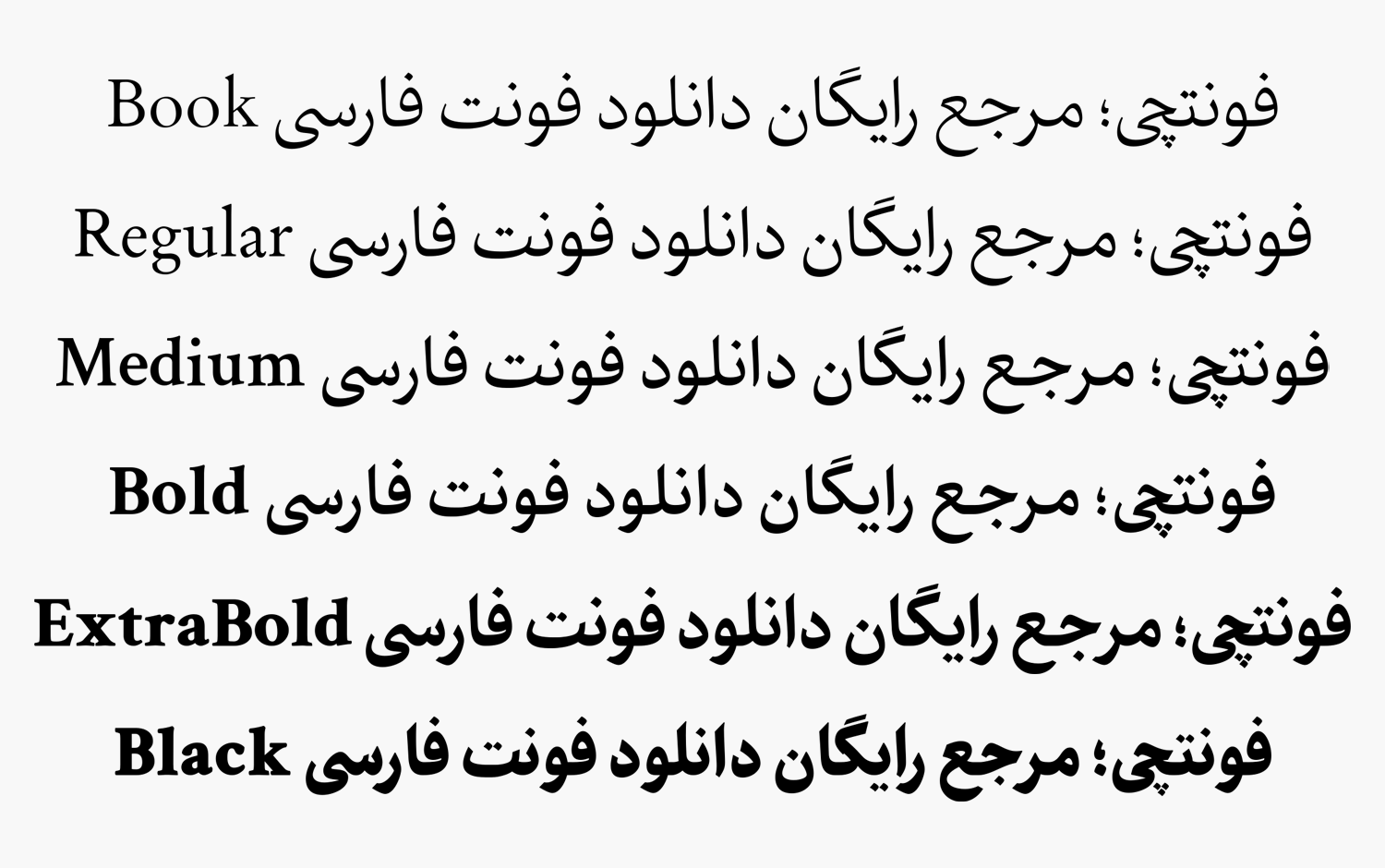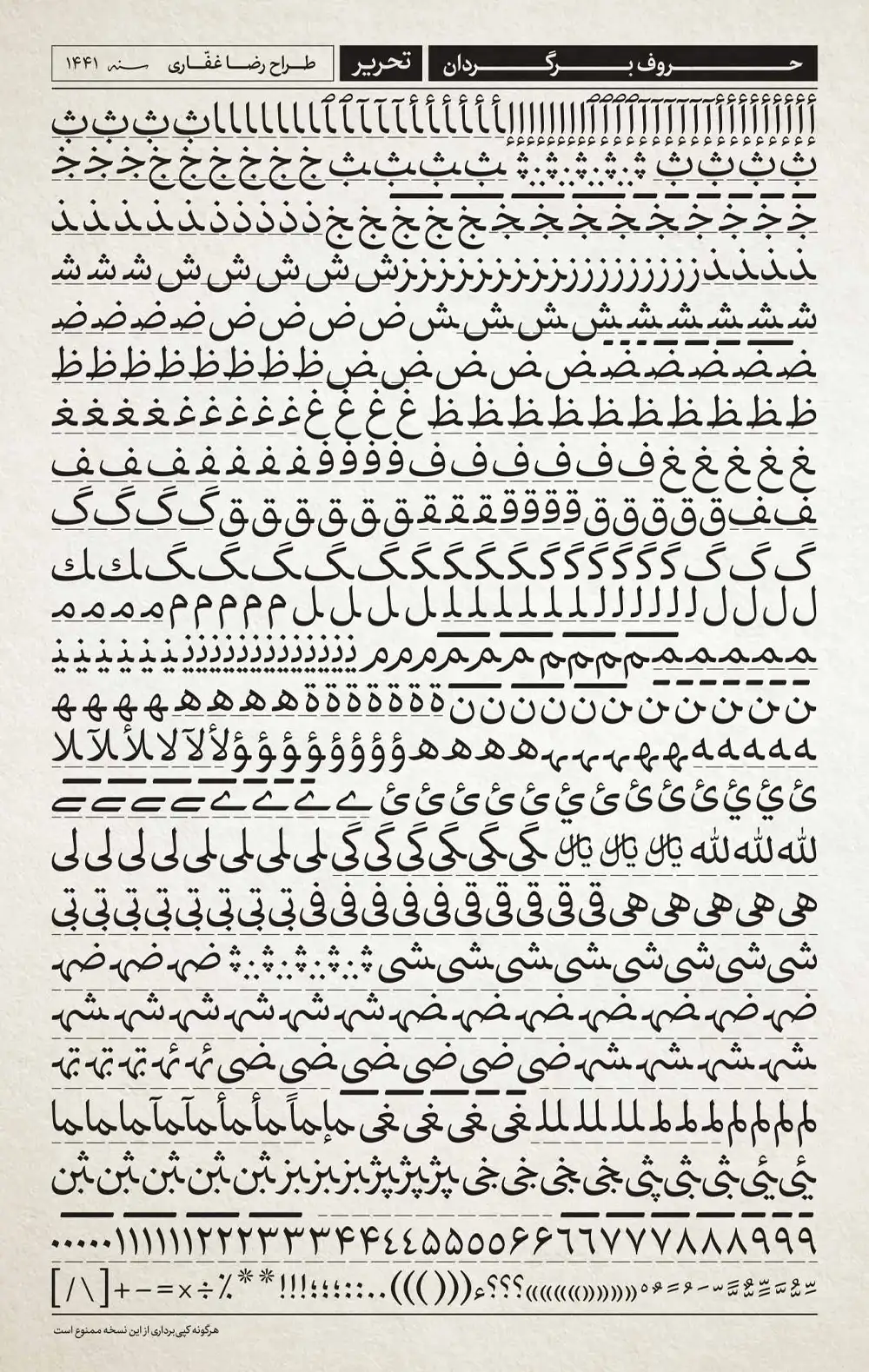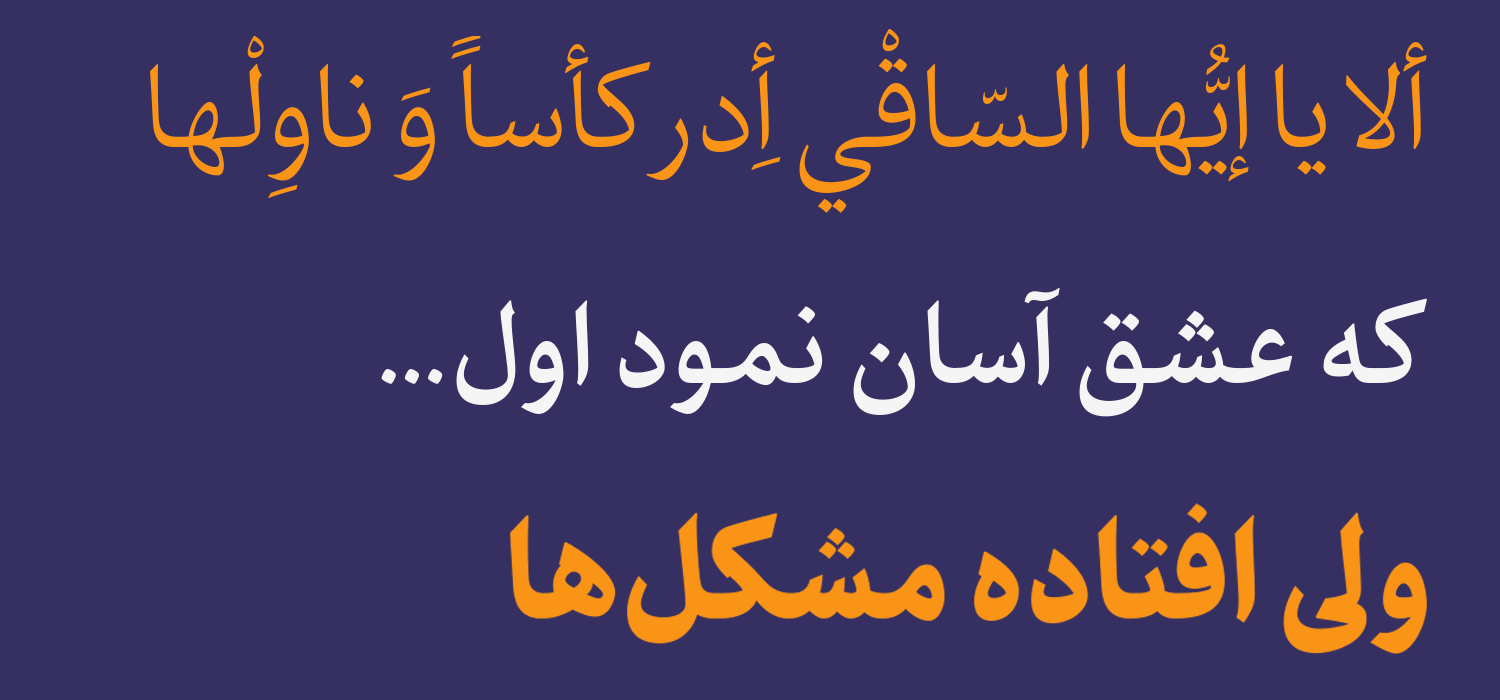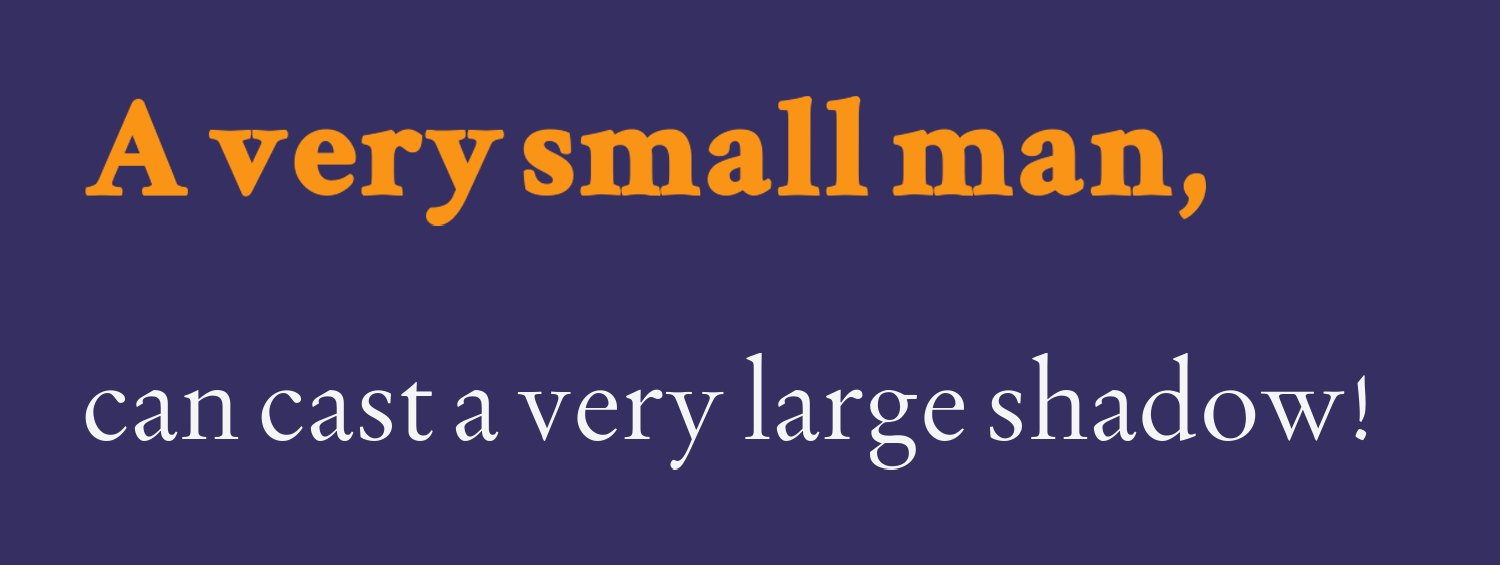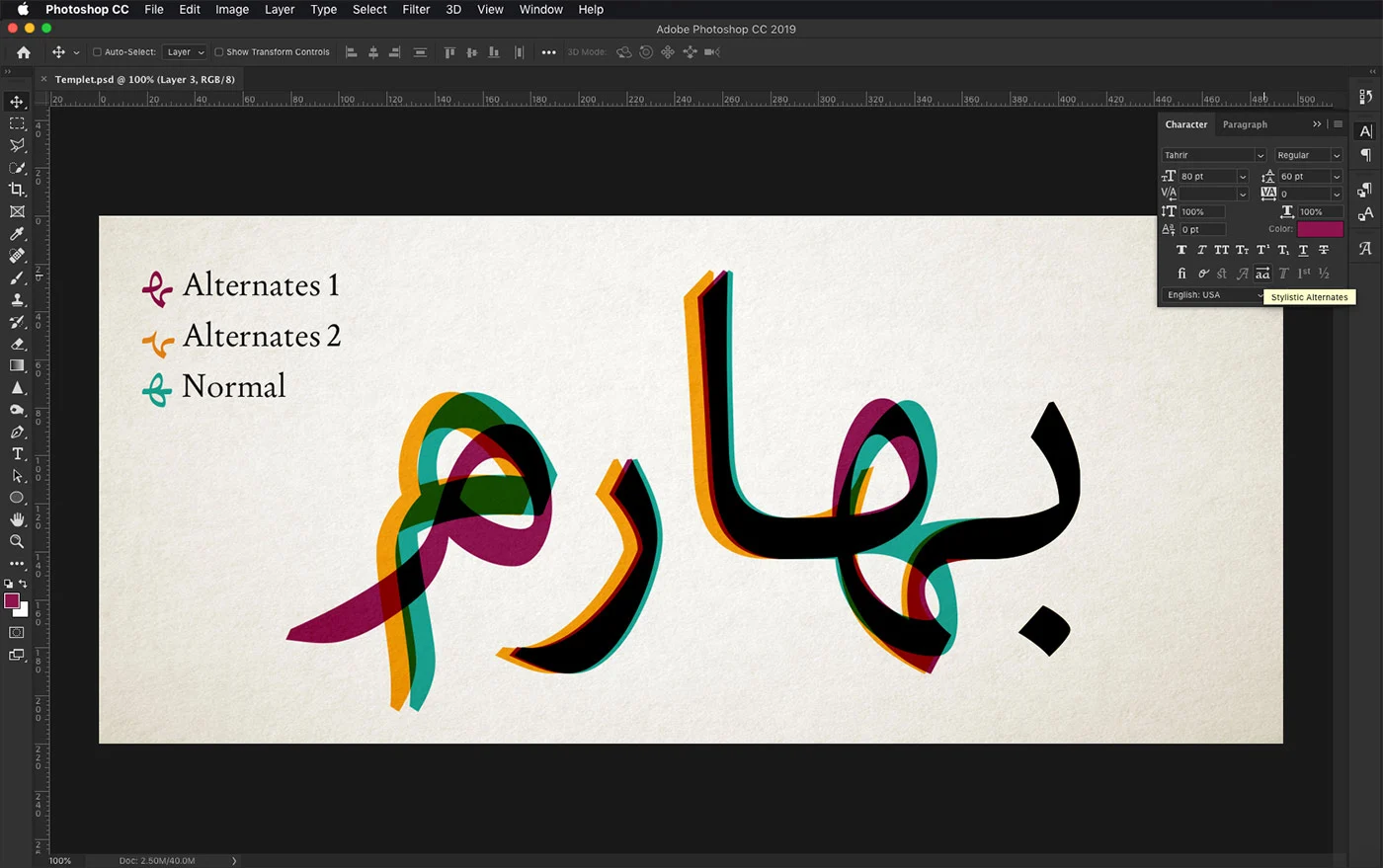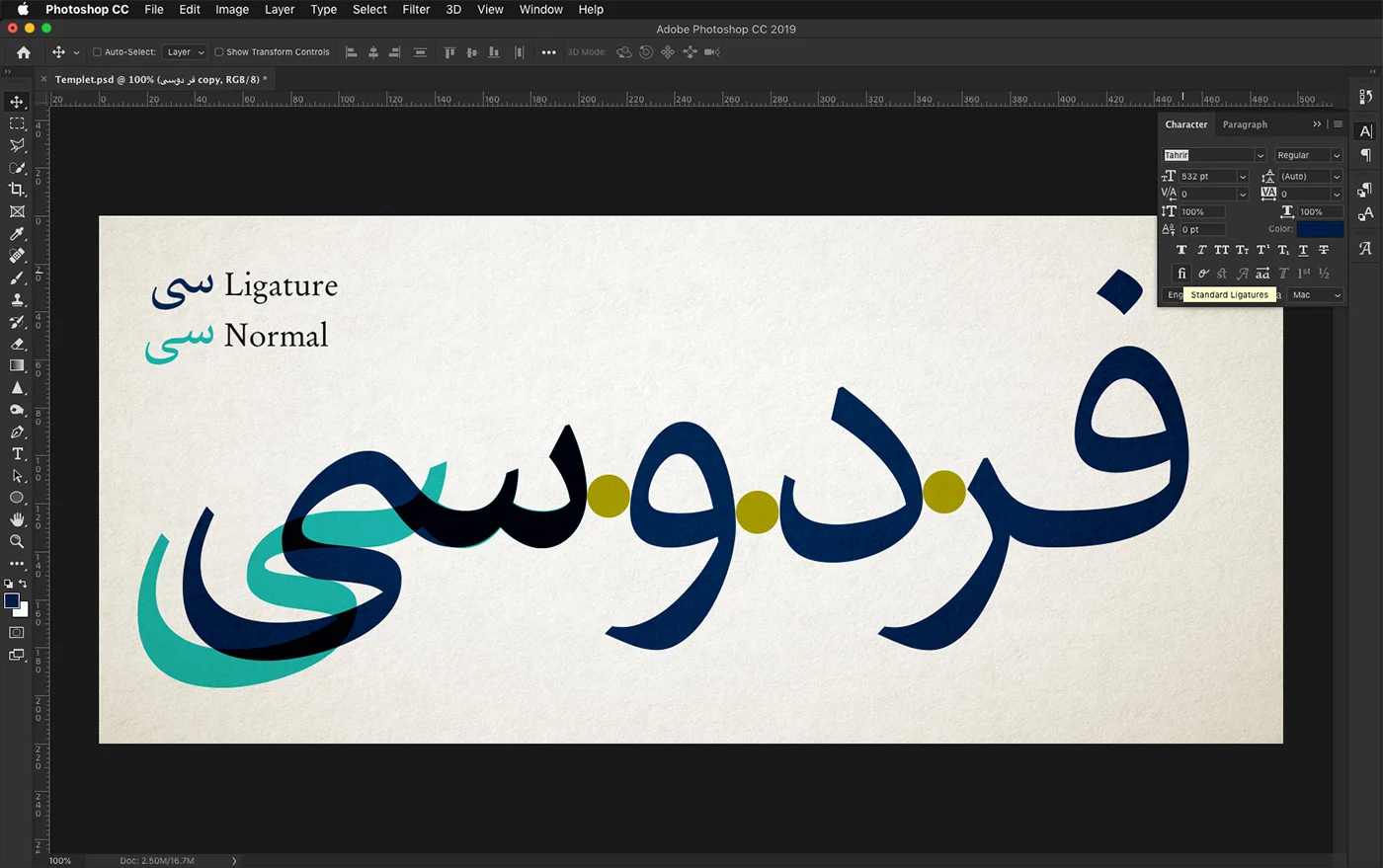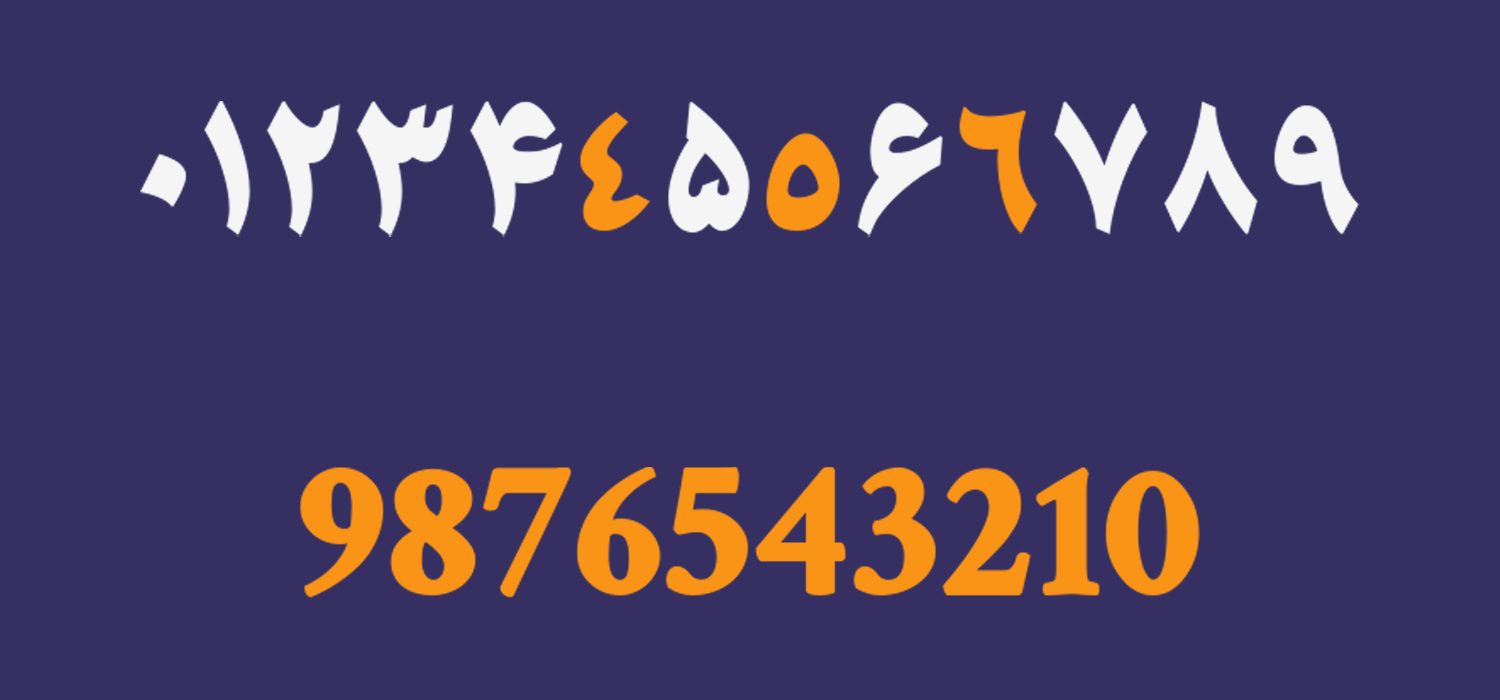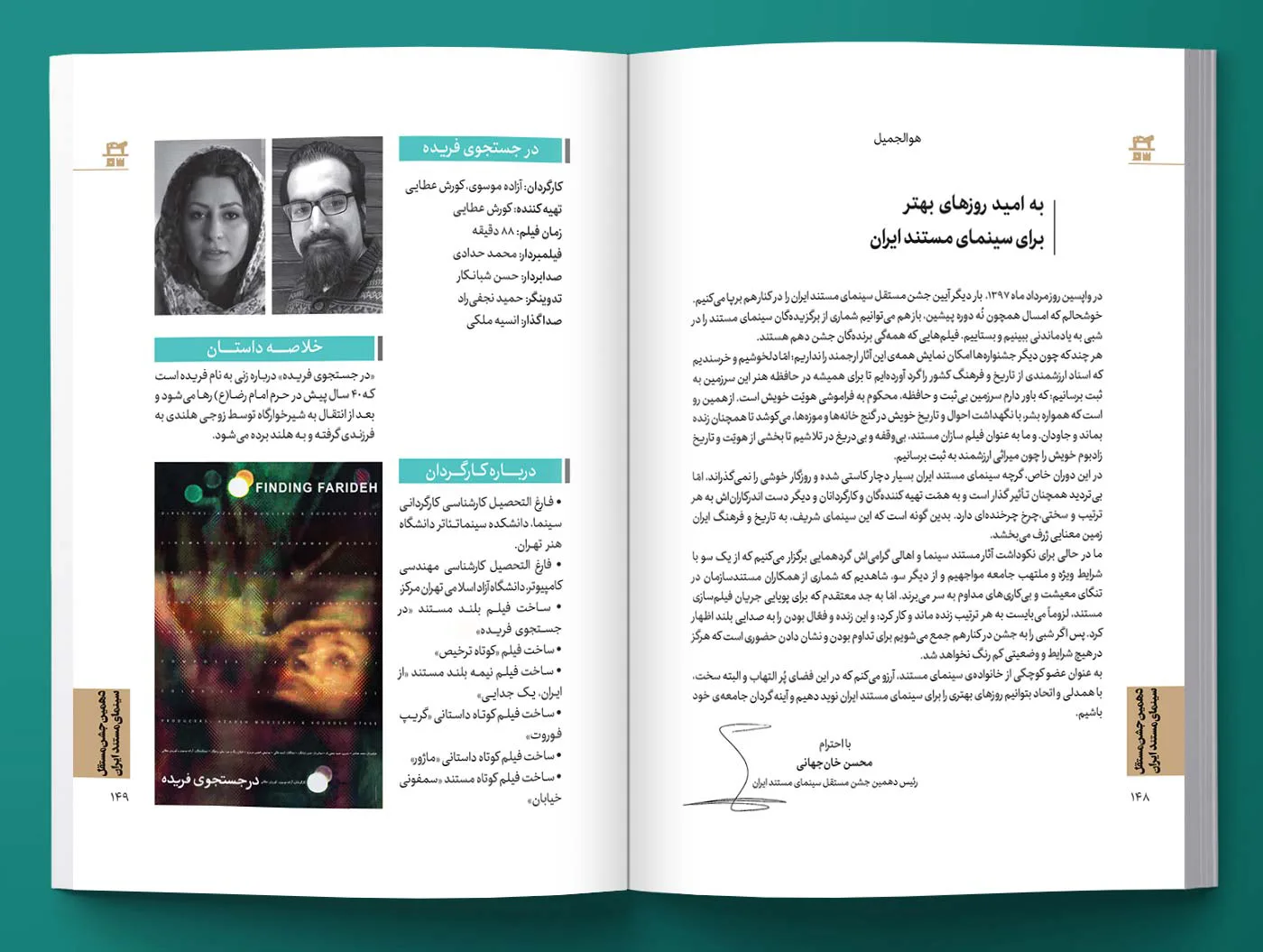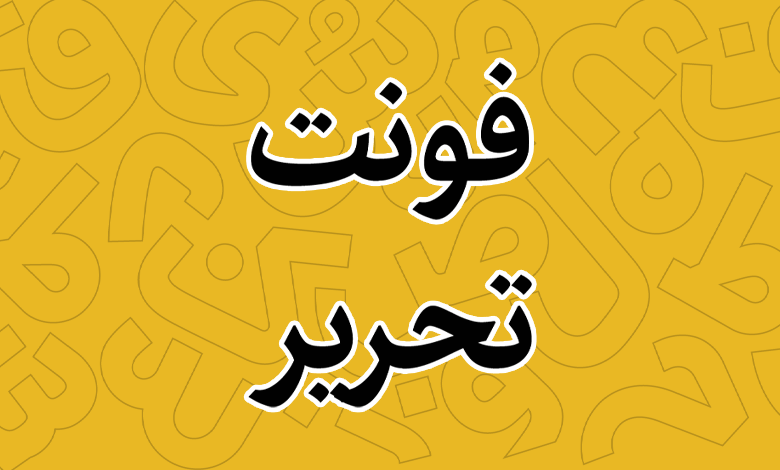
فونت تحریر (Tahrir)
فونت تحریر (به انگلیسی: Tahrir) در گروه فونتهای مناسب متن و مطبوعات قرار دارد که بر اساس خط نسخ در ۶ وزن مختلف طراحی شده است. این قلم همانطور که از نامش برداشت میشود برای استفاده در صنایع چاپ بیشترین کاربرد را دارد که شامل چاپ کتاب، روزنامه و مجلات، طراحی جلد و بیلبوردهای تبلیغاتی میشود.
توسعه و طراحی این قلم توسط رضا غفاری صورت گرفته است که یک تایپفیس بر مبنای زبان فارسی و عربی بوده که با توجه به رسمخط فارسی این قلم میتواند در تمامی زبانهایی بر اساس این خط مورد استفاده قرار گیرد و از زبانهای لاتین اروپایی و امریکایی نیز بههمین ترتیب پشتیبانی کامل دارد.
در ادامه این نوشته از سایت فونتچی به نقد و بررسی کامل فونت تحریر خواهیم پرداخت؛ قلمی که میتواند برای متون بلند مورد استفاده قرار گرفته و با توجه به پشتیبانی از چند وزن متنوع، ساختاری استاندارد را از نظر خوانایی در اختیار قرار دهد.
بررسی و دانلود فونت تحریر حرفه ای (Tahrir)
در طراحی و پیادهسازی خانواده فونت تحریر سعی بر این بوده است که با تنظیم نسبت ارتفاع و اندازه حروف و تنظیم نسبت دیگر کرسیها با هم، محصولی مطابق با نیازهای روز طراحی گرافیک و نشر رومیزی در اختیار کاربر قرار بگیرد. به همین جهت با یک فونت خاکستری مواجه هستیم.
الگوی کلی آن برای استفاده در پیکربندی روزنامهها، صفحهآرایی و طراحی کتاب، مجلات و بهطور کلی برای استفاده در متون طولانی چاپی طراحی شده است. همچنین تحریر در وزنهای تیرهتر به عنوان تایپ تیتر رسمی قابل استفاده در عناوین، سرفصلها و سوتیترها مناسب است.
اگر قرار باشد نمونه فونتهای نزدیک به این سبک را معرفی کنیم، فونت رایگان ساحل که ساخته صابر راستیکردار است نیز در این گروه قلمها قرار میگیرد که ضمن پشتیبانی از وزنهای مختلف، دارای نسخه وریبل است.
سبک طراحی و وزن فونت تحریر
در طراحی فونت تحریر خوانایی و زیبایی به یکاندازه اهمیت داشته است. جذابیتهای فرمی خط نسخ عربی و لحاظ کردن برتری نسبت دور به سطح در نسخ ایرانی نیز عامل مهمی در این جهت بوده است؛ که توانسته تحریر را به عنوان چهرهای تازه از خط نسخ چاپی معرفی کند.
با دیدن حروفچینی این قلم مطمئنا به یاد حروف برگردانهایی خواهید افتاد که تا دهه ۷۰ مورد استفاده قرار میگرفتند و حسی نوستالژی به شما خواهد داد. این قلم همان فونتی است که در آن حروفهای برگردان مورد استفاده قرار میگرفته است که حالا در قالب نرمافزار عرضه شده است.
این قلم از ۶ وزن مختلف پشتیبانی میکند و با توجه به اینکه قلمی اختصاصی برای صنعت چاپ است، دارای وزن پایهای به نام Tahrir Book است که در نامگذاری سایر فونتهای فارسی چنین وزنی را نداشتهایم. به همین ترتیب سایز وزنها نیز به ترتیب با افزایش ضخامت و تغییرات جزئی به این قلم افزوده است که تا وزن سیاه Black را شامل میشود که از این وزنهای ضخیم میتوان برای فونت عناوین و فونت تبلیغات استفاده کرد.
پشتیبانی کامل از زبان های مختلف فارسی و لاتین
فونت فارسی تحریر را میتوان کاملترین نسخه قلم فارسی در نظر گرفت که از این رسم خط پشتیبانی کاملی دارد که همین نیز عامل مهمی شده است تا از سایر زبانهای مبتنی بر این رسم خط پشتیبانی کند. البته ناگفته نماند که سعی طراح بر این بوده که دو زبان فارسی و عربی به صورت مشترک بیشترین هماهنگی را داشته باشند که خود این مسئله عامل مهمی برای پشتیبانی از سایر زبانها بوده است.
در زبان عربی فونت تحریر ضمن اینکه از تمامی حروف مشترک فارسی پشتیبانی میکند، سایر حروفی مثل «ک، ی، ه، ؤ، ئ» که ساختاری متفاوت از نظر قرارگیری نقطه و همزه نسبت به زبان فارسی دارند پشتیبانی میکند.
اعراب در این زبان در یک هم نشینی منظم با تشدید، همزه و سکون را دارند که خود به خوانایی متن و زیباتر کردن ترکیبات کمک میکند.
تحریر با پشتوانه بر همین دو زبان از سایر زبانهای کردی، اردو و ترکی نیز پشتیبانی میکند که برای زبان اردو حروفی همچون «ﮧ، ﮩ، ے» ضمن پشتیبانی استاندارد به عنوان حروف جایگزین برای سایر زبانها نیز قابل استفاده هستند.
قلم تحریر طبق استاندارد جهانی یونیکد ساخته شده که ضمن پشتیبانی از تمامی محیطهای متنی و نرمافزاری برای زبانهای فارسی، در زبانهای لاتین همچون انگلیسی نیز بر اساس ساختارهای مختلفی که برای زبانهای امریکایی و اروپایی قرار دارد پشتیبانی کاملی خواهد داشت.
دارای ترکیبات و حروف جایگزین بسیار متنوع
ویژگی دیگر فونت تحریر پشتیبانی از ترکیبات و حروف جایگزین است که امکان تایپ کلمات را با ظاهر مختلفی فراهم میکند. به عنوان نمونه مشابه تصویر زیر میتوانید برای دو حرف «ه، م» در حالتی که در ابتدا، میانه یا انتهای کلمات درج شده باشند از ۳ حالت جایگزین مختلف استفاده کنید که برخی از این حالات همان ساختار حرف «ﮧ، ﮩ» در زبان اردو هستند.
تایپ اینگونه حروف جایگزین ضمن اینکه به خوانایی، زیباتر شدن و ایجاد یک تفاوت در برخی کلمات نسبت به سایر کلمات موجود در جملات کمک میکند، باعث جلب توجه بیشتر کاربر خواهد شد که در حوزه چاپ میتواند روی فروش بهتر محصول موثر باشد.
یا در نمونه دیگری مشابه تصویر زیر امکان تایپ ترکیبات «ـی، سی، شی، صی، ضی» را در دو حالت زیر خواهید داشت که شامل نسخه معمولی Normal و نسخه لیگچر Ligature میشود.
این ترکیبات و حروف جایگزین در فونت تحریر محدود به این موارد نیست و با توجه به تصویری که در ابتدای نوشته برای حروفچینی قلم درج شده شامل حروف دیگری همچون «س، ش، ک، گ، ی» در حالات مختلف تکی و همراه با ترکیبات دیگر میشود.